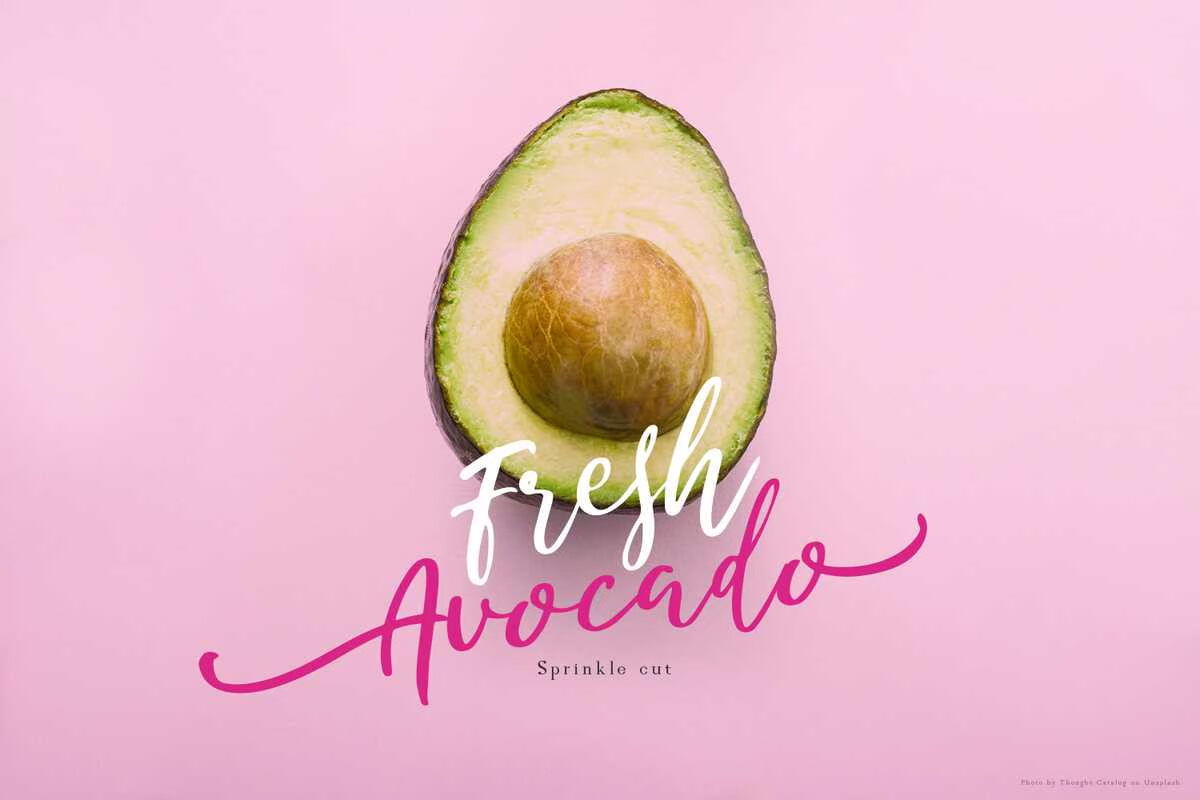
Romello是为了让您的设计更有趣、更漂亮而设计的漂亮类型面。Romello还与用于装饰所有文字的替代性字符相匹配,Romello是张贴设计、签名、徽标、报价、专辑封面、名片、产品设计的完美选择之家,还有许多其他的设计项目。使用时,加州的Kallimatamodernhas也在使用中。我们让这款Font看起来优雅、优雅、易读、时尚、易记且简单。Romello是一个漂亮的方面,它让你的设计看起来更有趣、更漂亮。Romello同时也是一个替代性的角色,可以美化所有的写作,Romello是完美的后期设计之选,签名、徽标、报价、专辑封面、名片、产品设计以及其他许多设计项目。使用时,Kallimatamodernhasistowncharm。我们使这款Font看起来优雅、优雅、易读、时尚、易记且简单。